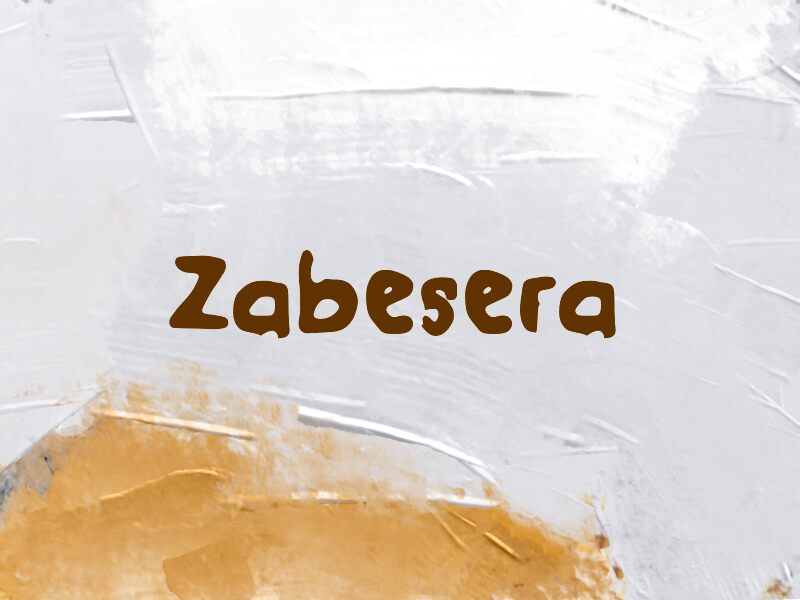
Zabesera od Wep je bezplatné písmo typu brush, kterému dominují široké, zaoblené tahy přecházející do měkkých, inkoustových skvrn. Rytmus působí uvolněně a ručně malovaně, s baňatými křivkami a lehce nepravidelnými okraji, díky nimž písmo nepůsobí příliš uhlazeně nebo kaligraficky.
Tato výrazná textura dává krátkým nadpisům sílu, ať už jde o plakáty, branding kaváren, etikety produktů, grafiku na sociální sítě nebo neformální obaly. Skvěle se hodí také na samolepky či merchandising, kde její buclaté malované tvary vnášejí do designu přátelský a domácký nádech, aniž by sklouzávaly k úhledné klasice.
Zabesera
Prezentace a vizuální ukázka písma Zabesera